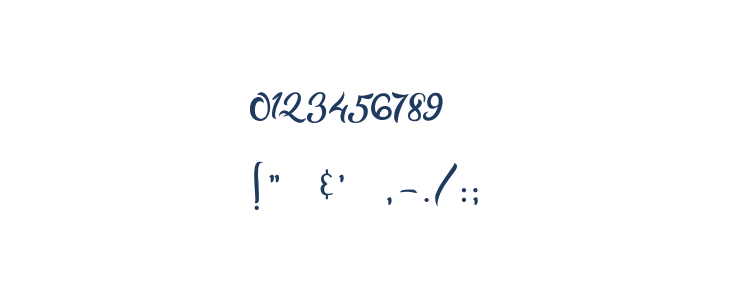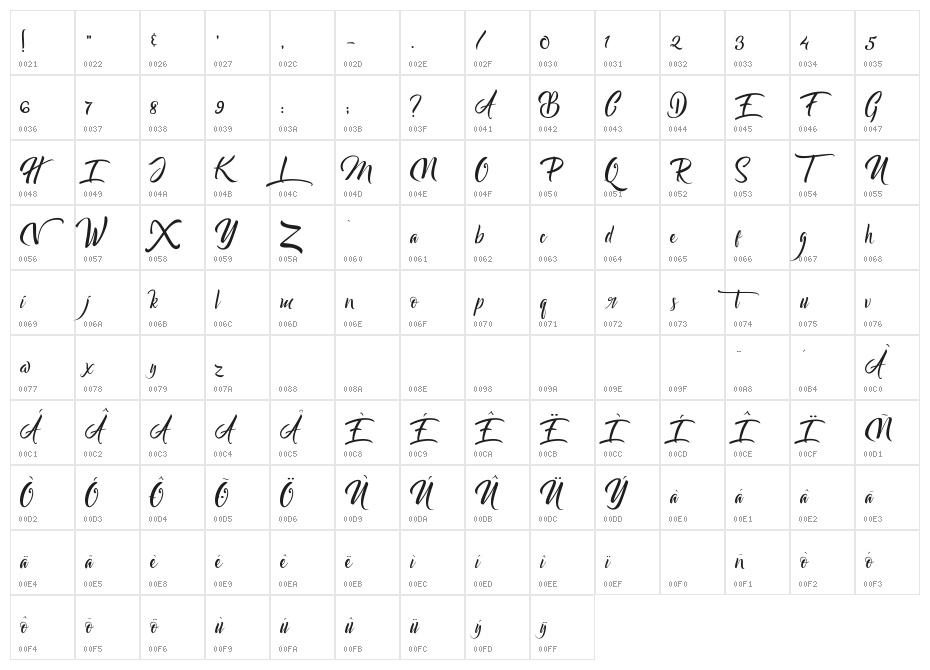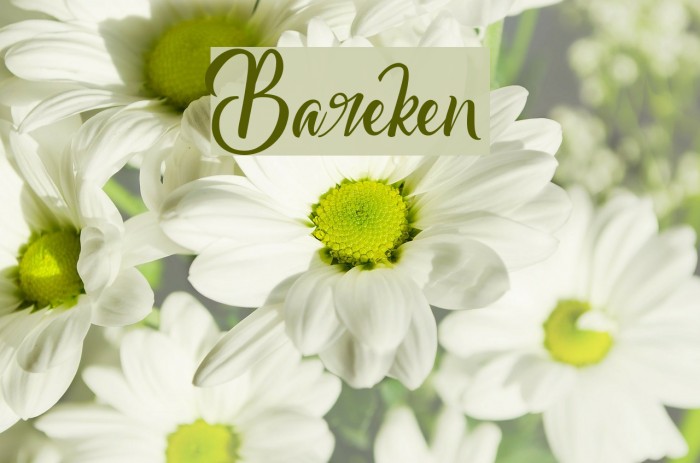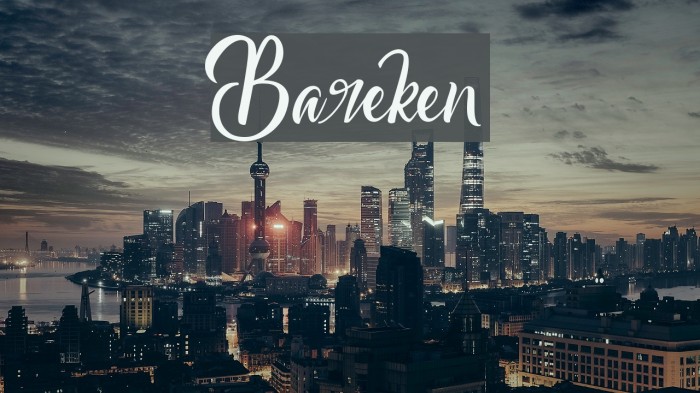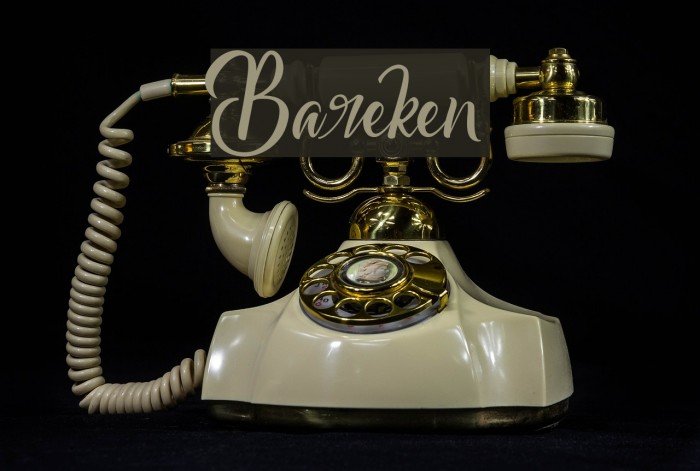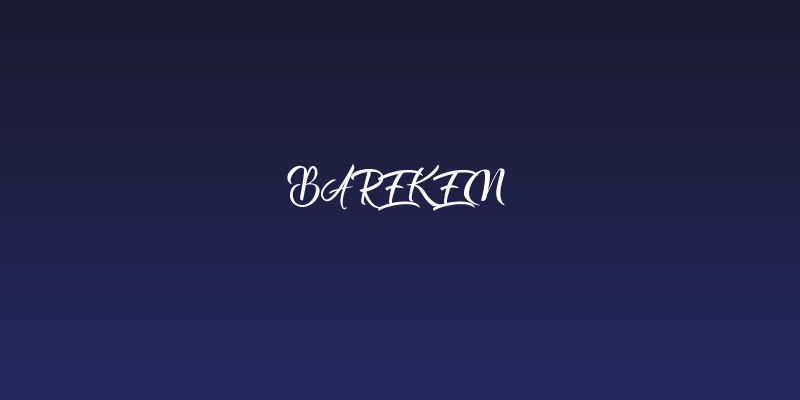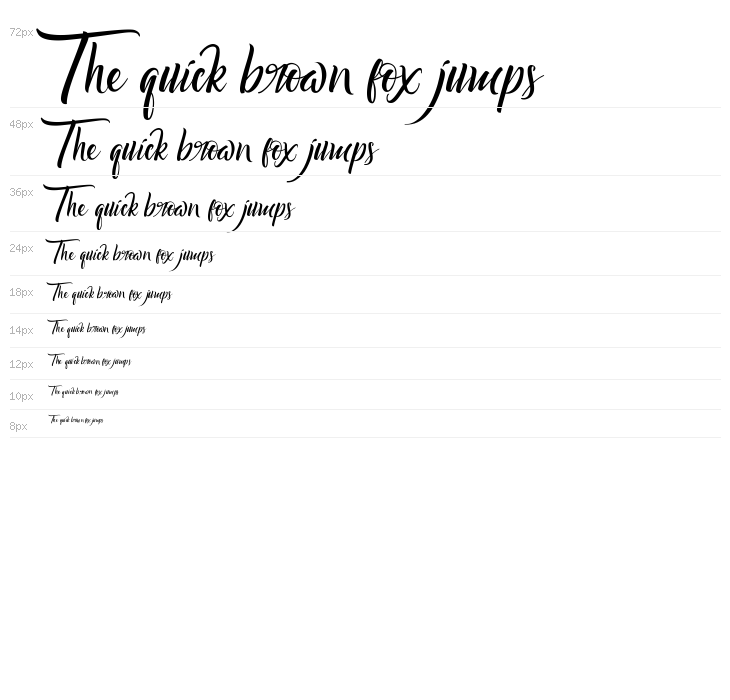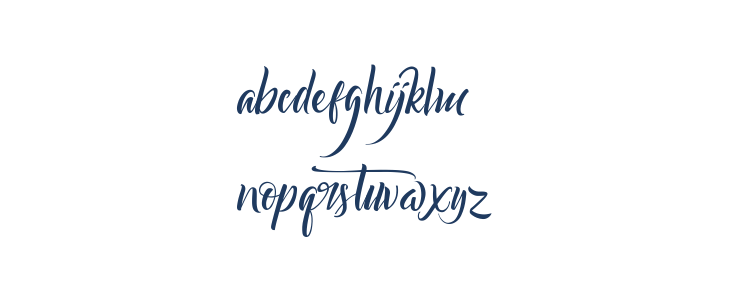
Bareken Font
| Caso d'uso | Logos, Invitations, Decorative text |
| Progetti proposti | Ideal for wedding invitations, greeting cards, branding projects, and elegant packaging designs. |